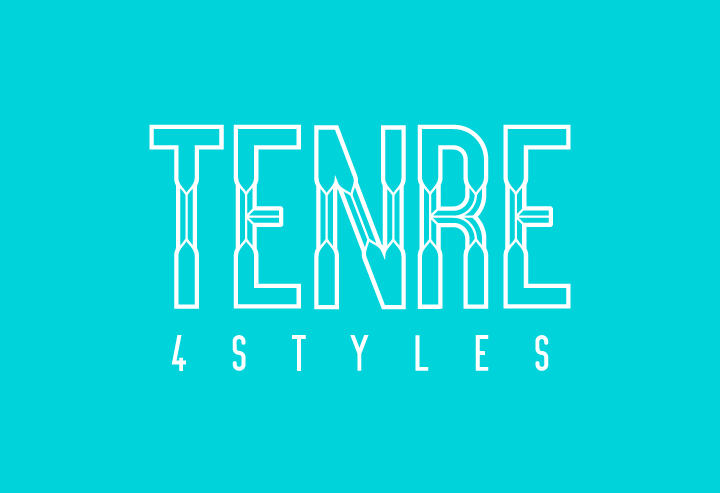
A TENRE Font é uma opção perfeita para designers que buscam uma tipografia sem serif com um toque vintage moderno. Esta família de fontes em estilo sans-serif apresenta quatro estilos distintos e está disponível para uso tanto na web quanto em impressão, garantindo a legibilidade e elegância necessárias para qualquer projeto. Desenvolvida pelo designer Hamilton, a TENRE oferece um toque vintage que transborda de modernidade. Seus detalhes sutis e linhas finas evocam o passado enquanto se equipa com características assertivas e uma aparência futurista. Esta fonte é perfeita para aplicações variadas, desde banners exuberantes até design editorial sofisticado. Com sua arquitetura elegante e texturas distintas, a TENRE não apenas oferece estilos distintos, mas também se adapta facilmente aos diferentes contextos de uso, garantindo que o texto seja sempre claro e de fácil leitura. Perfeito para criar projetos com um toque único, essa fonte é uma ótima escolha tanto para designers iniciantes quanto para profissionais experientes em busca de uma nova inspiração.